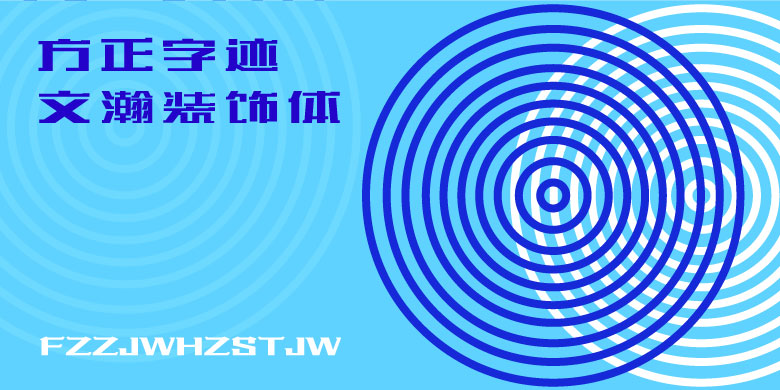
方正字迹-文瀚装饰体
字体介绍:
目前,行业专属字体很少,比如包装行业基本涵盖各行各业,建筑业占全国半壁江山,传媒行业,图书、报纸、电视、网络等包括诸多行业都应该有各自不同的风格各异的字体。缘于此,分别试设计出“包装体” 、“建筑字体”、“传媒字体”“装饰字体”等和其它美术字体。<br>方正字迹-文瀚装饰体源于装饰行业的专业名词。家装设计,设计师们都喜欢做曲线吊顶设计,字体装饰性很强,便称之为装饰字体。 其创意设计是把它做成一款统一、和谐的字体,以便丰富艺术形象,扩大艺术表现力,加强审美效果。设计装饰字体,对称是必须的,字体的创意是以长方形结构见长,字笔上加一些装饰,但必须简洁,规范。只有这样,字体既有装饰性很强,又有大方明快之感。装饰涵盖了生活的方方面面,在现代生活中,装饰无处不在。所以,装饰字体的用途非常广泛,基本都可以用在见到文字的地方。